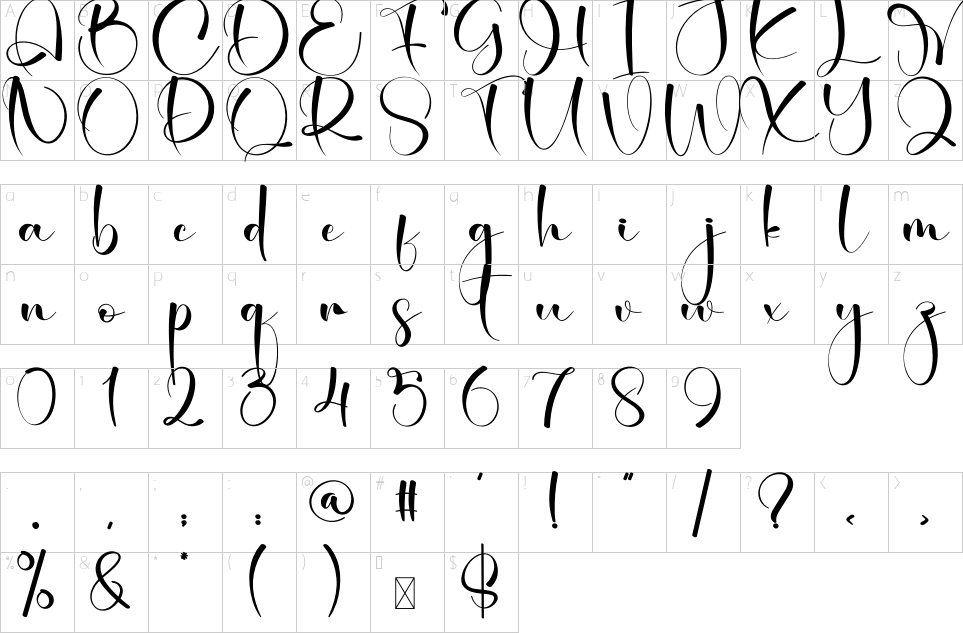
A Montbel é uma fonte moderna e elegante que oferece uma experiência visual fluida tanto para os usuários de Windows quanto para os de Mac. Criada por um designer não identificado, ela se destaca por sua simplicidade e beleza, combinando elementos agradáveis que podem melhorar a aparência de qualquer projeto. Esta fonte foi baixada mais de 475 vezes, evidenciando seu potencial como uma escolha versátil para designers e criadores de conteúdo. Com seu design limpo e versátil, a Montbel é perfeita para uso em sites, e-books, aplicações web e qualquer outro tipo de material digital. Engaje-se com a Montbel e dê uma nova vida ao seu design, oferecendo aos seus usuários uma experiência visual agradável e única.